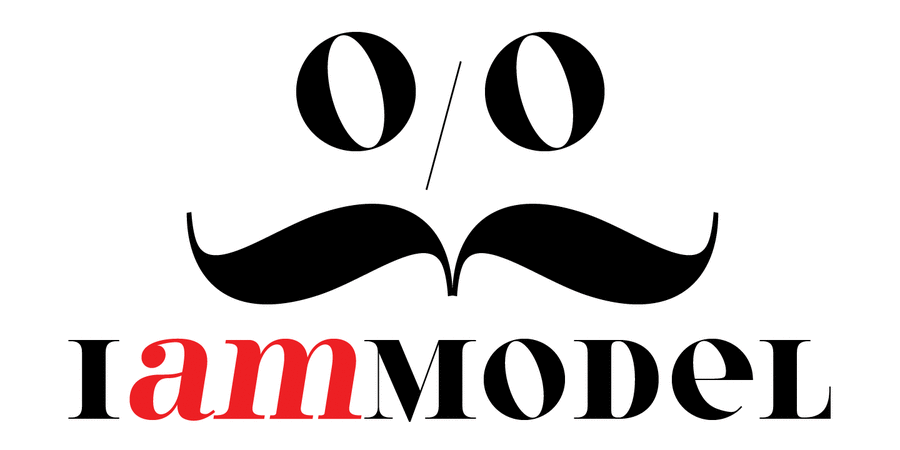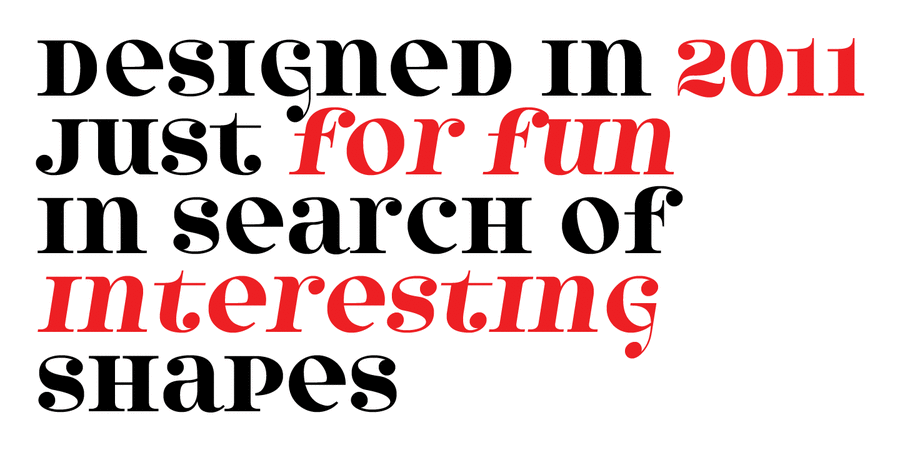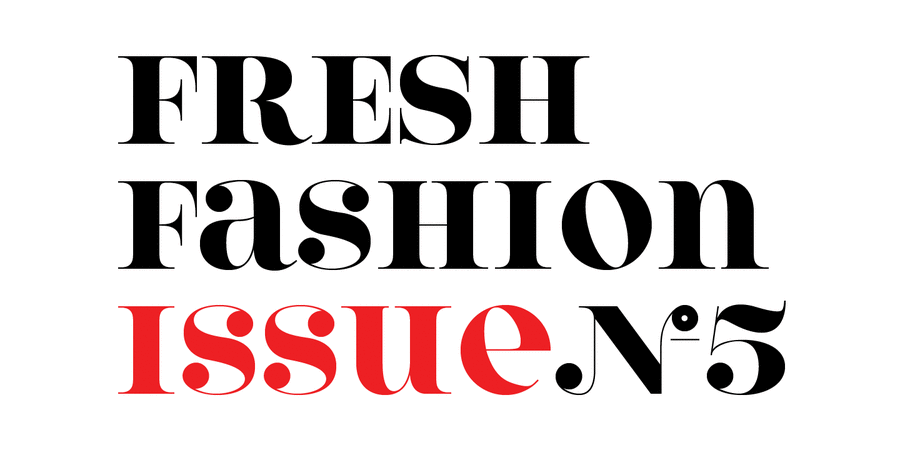
Опис гарнітури Model 4F UnicaseШрифт для заголовков, плакатов и журналов. Разработан Сергеем Ткаченко в 2011 году.
Асоціації з сімейством шрифтів Model 4F UnicaseОсобистість і характер гарнітури:
ефектний, вишуканий, оригінальний, модний, гламурний, святковий, блискучий, розкішний, багатий, гострий, глянцевий, характерний, манірний, претензійний, пластичний, салонний, сексуальний, романтичний, майстерний, красивий, яскравий, привабливий, витончений, дзвінкий, ювелірний, екстравагантний, естетський, нонконформістський, експериментальний, гордий, театральний, драматичний, пристрасний, динамічний, гарненький, симпатичний, дорогий, добірний, елітний